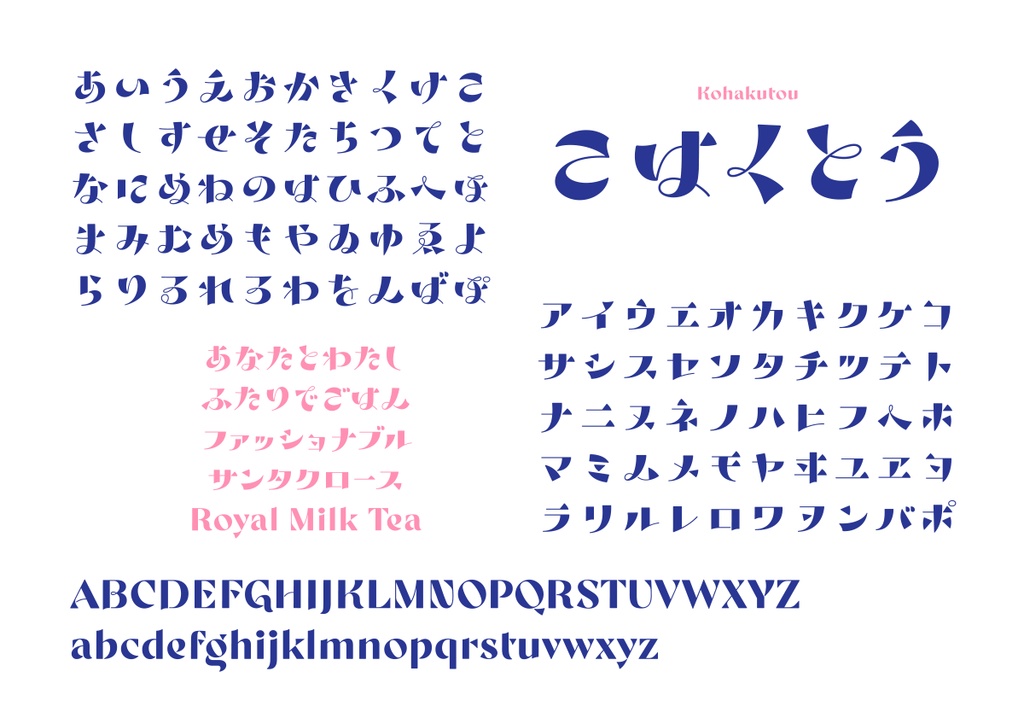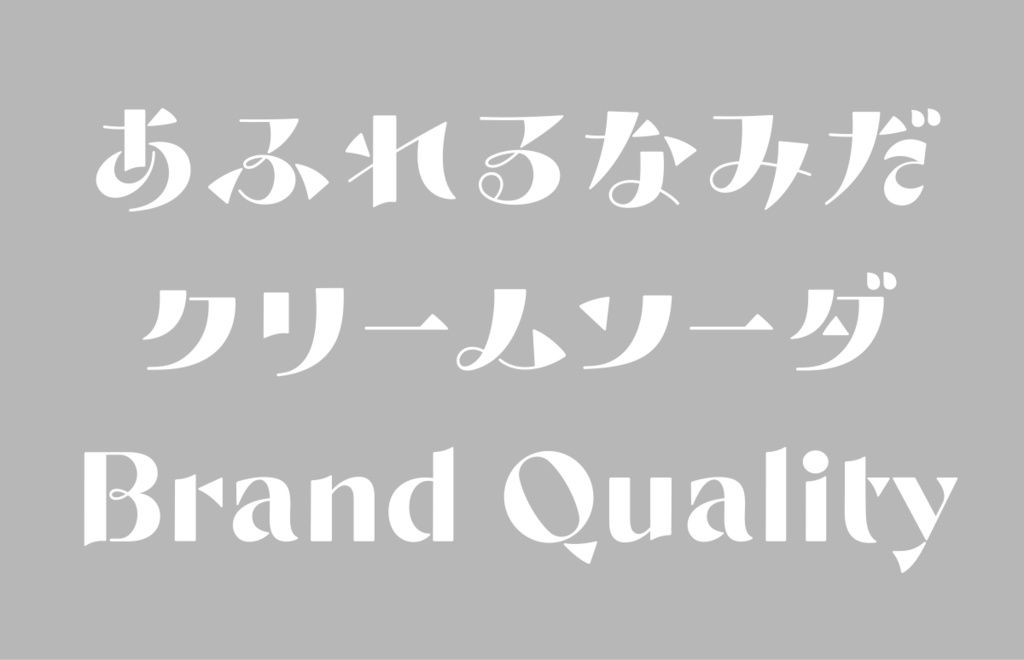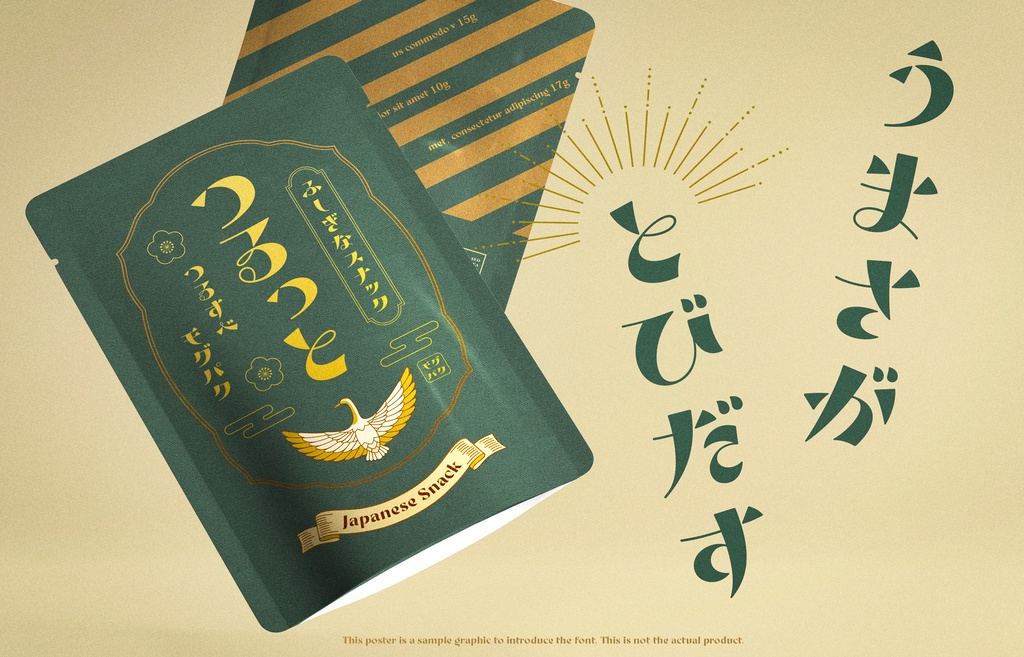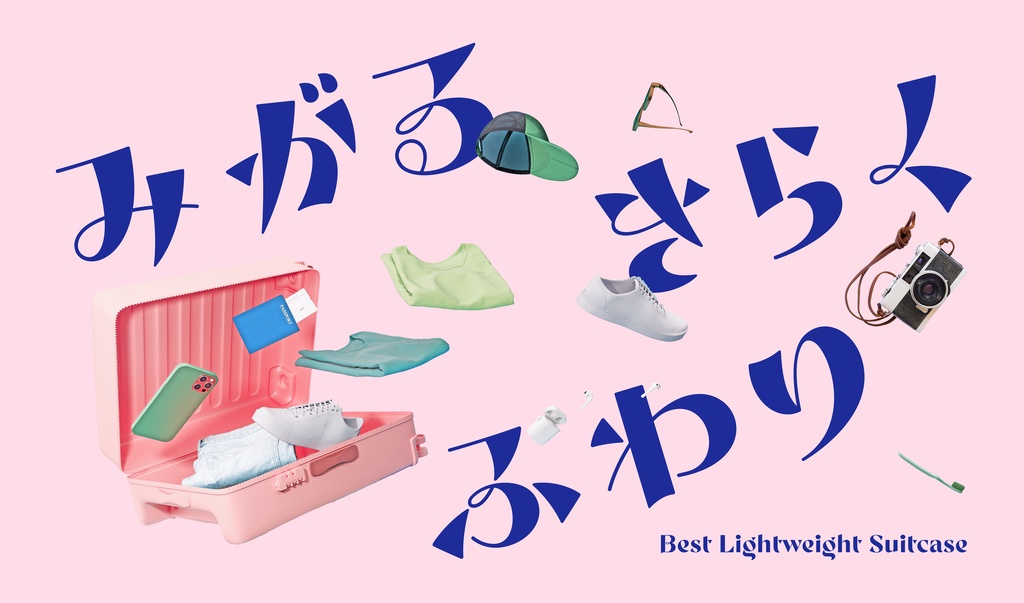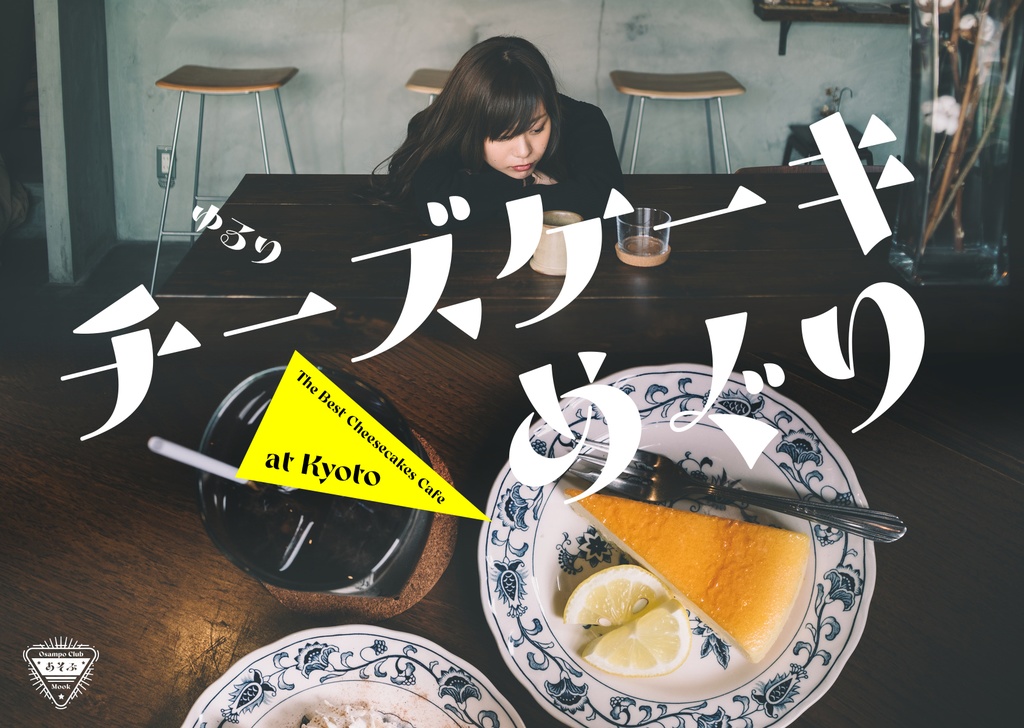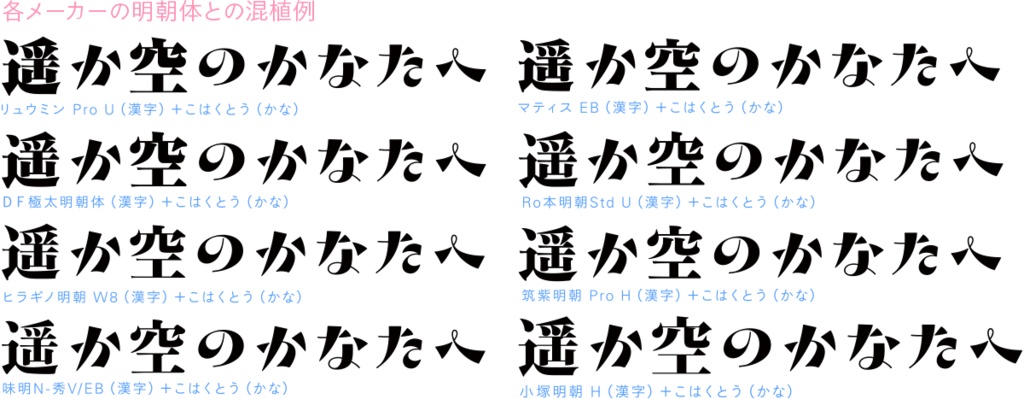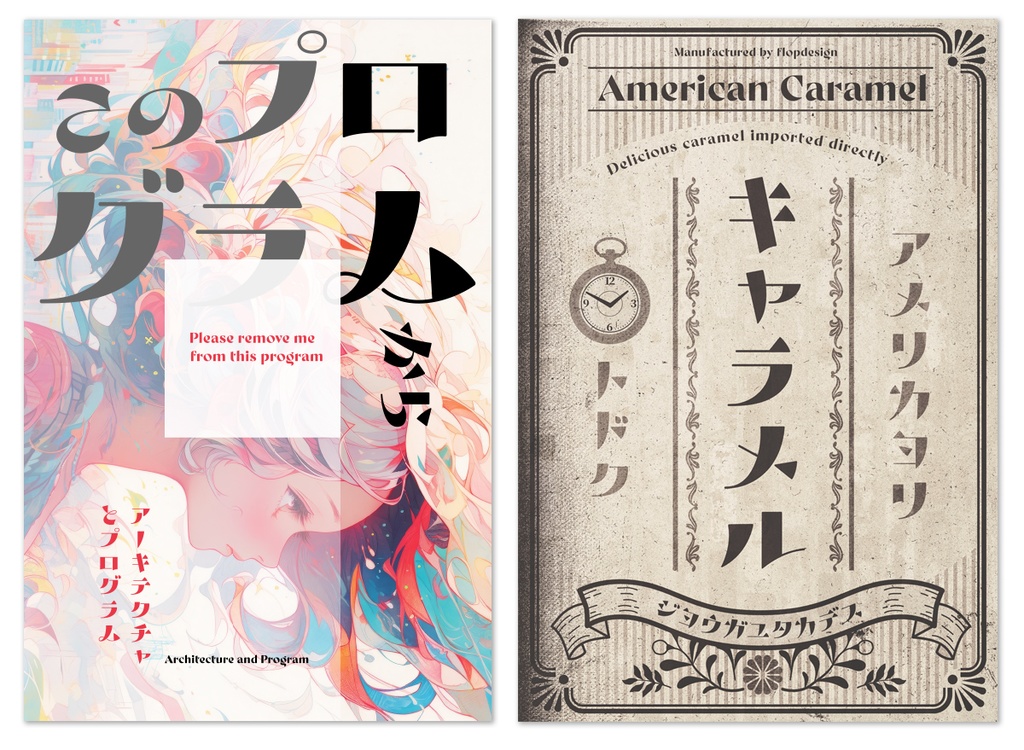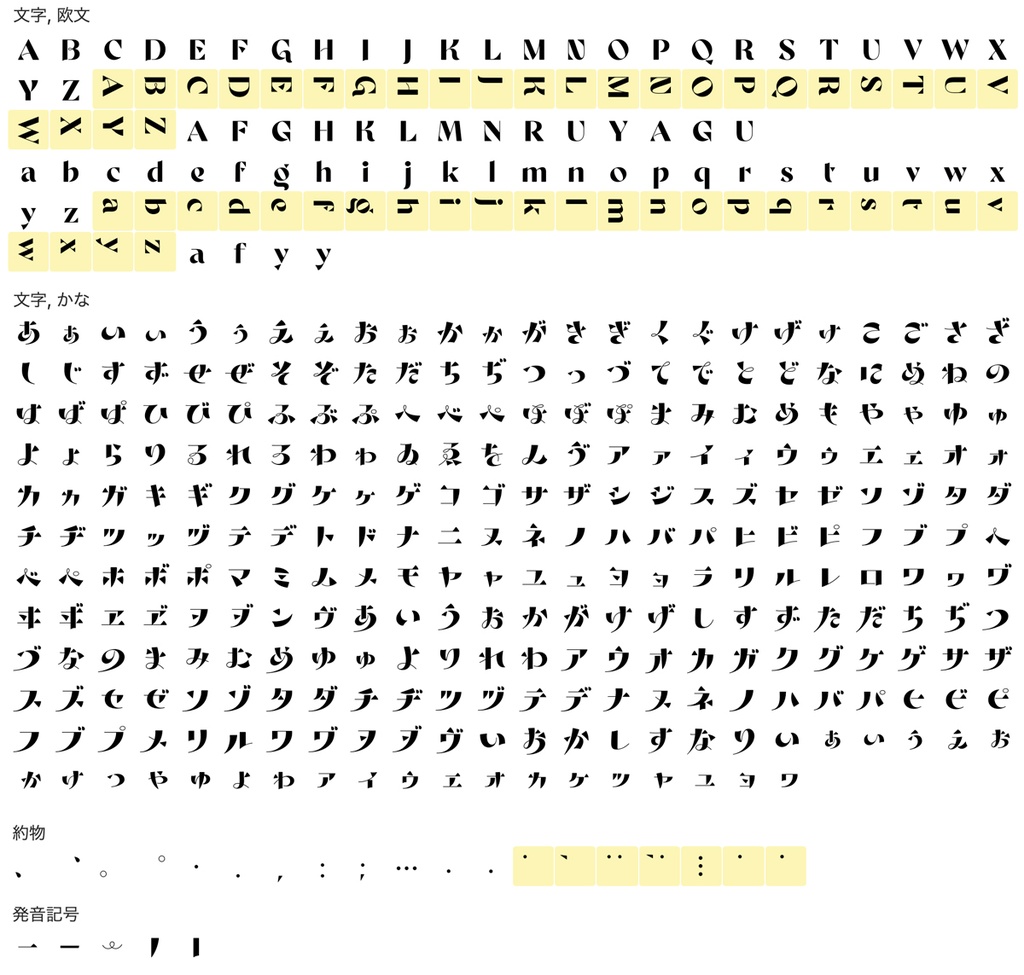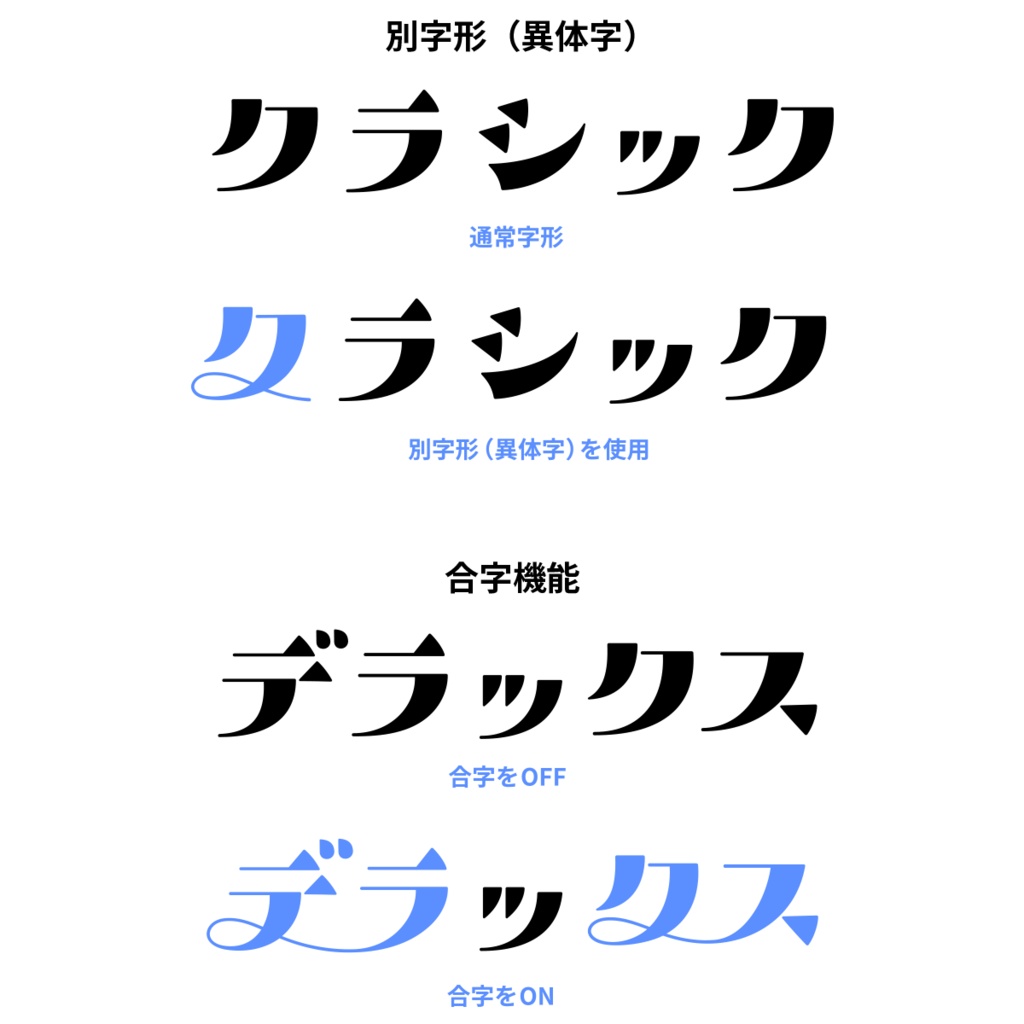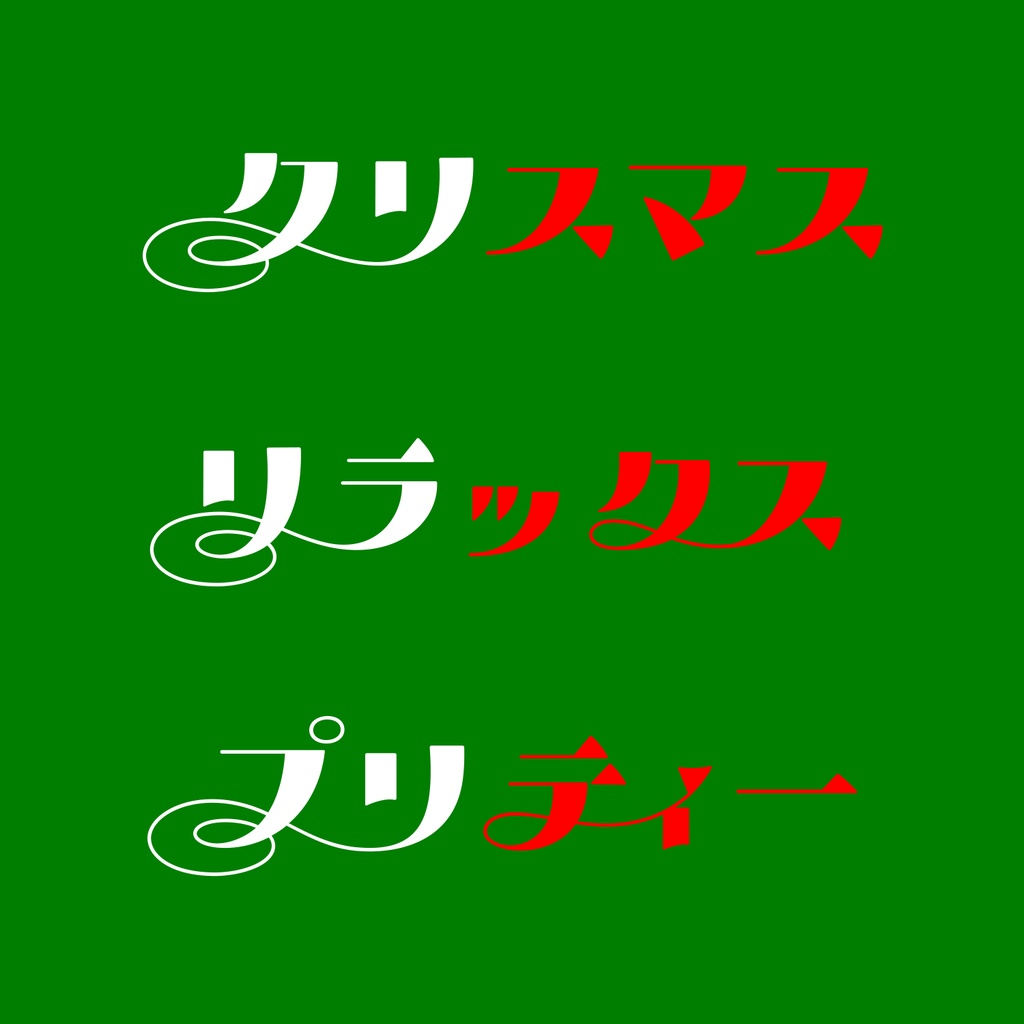
こはくとう フォント
超極太のポップ系明朝体。三角形のエレメントとループした細いラインの組み合わせが特徴。極太と細い線のコントラストが明快なデザインは、インパクトがあり印象的なデザインが可能です。ロゴデザイン、チラシ、書籍への使用などで大活躍。日本タイポグラフィ年鑑2025入選作。 ■動作環境 Mac:システム/OS X対応(10.x)〜最新のOS X Windows:OS/日本語版Windows2000、XP、VISTA、Windows7〜11以降 フォント形式:OpenTypeフォント 1商品(1ライセンス)につき1ユーザー1PCのみがご利用いただけます。人数分をご購入ください。 ■収録文字について 収録文字数730字。アルファベット、ひらがな、カタカナ、約物の一部。 ■安心して使えるロイヤリティフリーの書体 商用・デザイン用途(印刷物・ゲーム・アプリ・映像・動画・ロゴ・同人作品)に使用できる、商用申請の必要のないロイヤリティフリーの書体になります。文字の加工・変形も可能です。ご安心ください。 ■OpenType機能 詰め組み機能 ペアカーニング(仮名・プロポーショナル欧文) 字形切り替え機能(異なる字形を198種用意しています) 合字(151文字) ※字形切り替えと合字が使えないソフトウェア用に追加のフォントファイルとPDFデータを用意しています。